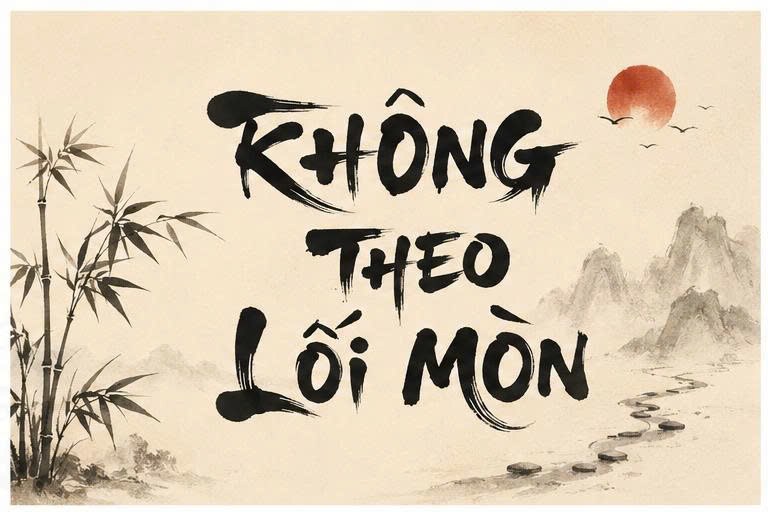
Download font chữ thư pháp là nhu cầu hàng đầu của các designer khi bước vào mùa thiết kế bao bì Tết, thiệp chúc mừng hoặc các ấn phẩm văn hóa truyền thống Á Đông. Khác với các dòng phông chữ hiện đại, font thư pháp mang trong mình cái hồn của nét mực tàu, sự bay bổng của bút lông và sự uy nghi của nghệ thuật chữ viết tay. Doozypack.vn tổng hợp và chia sẻ link tải font thư pháp Việt hóa trọn bộ, giúp bạn hiện thực hóa các ý tưởng thiết kế hộp quà, bao lì xì hay logo thương hiệu mà không lo lỗi dấu tiếng Việt.
Tổng hợp các bộ font chữ thư pháp đẹp và phổ biến nhất
Hệ thống font thư pháp rất đa dạng về phong cách, từ những nét chữ mộc mạc, xưa cũ đến những đường nét thanh thoát, hiện đại.
Font thư pháp Ông Đồ – Nét chữ hoài cổ kinh điển
Khi nhắc đến download font chữ thư pháp ông đồ, người ta nghĩ ngay đến những nét chữ dày, đậm và có phần hơi rung nhẹ, mô phỏng lại cách viết của các bậc túc nho ngày xưa. Đây là lựa chọn số một để thiết kế tiêu đề cho các loại bánh mứt truyền thống, câu đối đỏ hoặc các ấn phẩm mang phong cách “Sài Gòn xưa”.
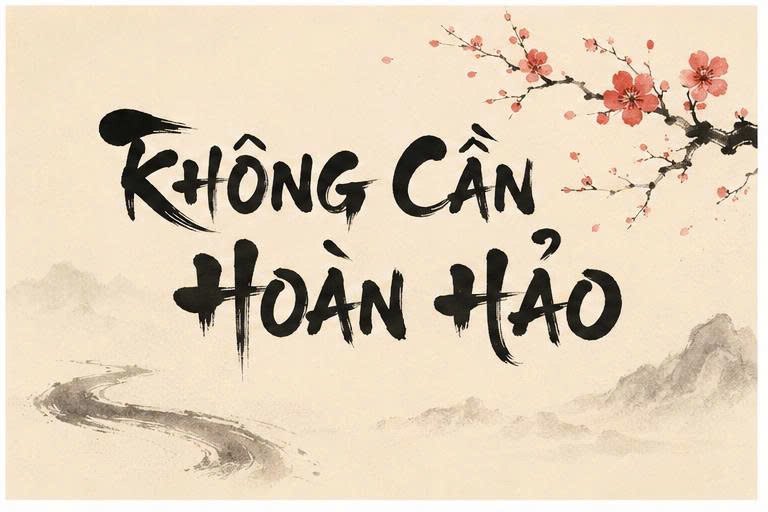
Font thư pháp Thiên Ân – Tinh tế và bay bổng
Nếu bạn cần sự nhẹ nhàng và nghệ thuật hơn, tải font thư pháp Thiên Ân là gợi ý tuyệt vời. Bộ font này nổi tiếng với các đường hất bút thanh mảnh, liên kết mượt mà giữa các ký tự, tạo nên một dòng văn bản trôi chảy. Thiên Ân thường được ứng dụng trong thiết kế thiệp mời sự kiện văn hóa, nhãn rượu vang hoặc hộp quà tặng cao cấp.
Font chữ Trung Quốc thư pháp – Nghệ thuật Á Đông
Với các dự án bao bì xuất khẩu hoặc sản phẩm mang phong cách cổ phong, việc tải font chữ Trung Quốc thư pháp giúp tạo điểm nhấn bản sắc mạnh mẽ. Các phông chữ này mô phỏng chân thực các lối viết Triện, Lệ hay Hành thư, giúp nhãn mác sản phẩm toát lên sự lâu đời và uy tín.